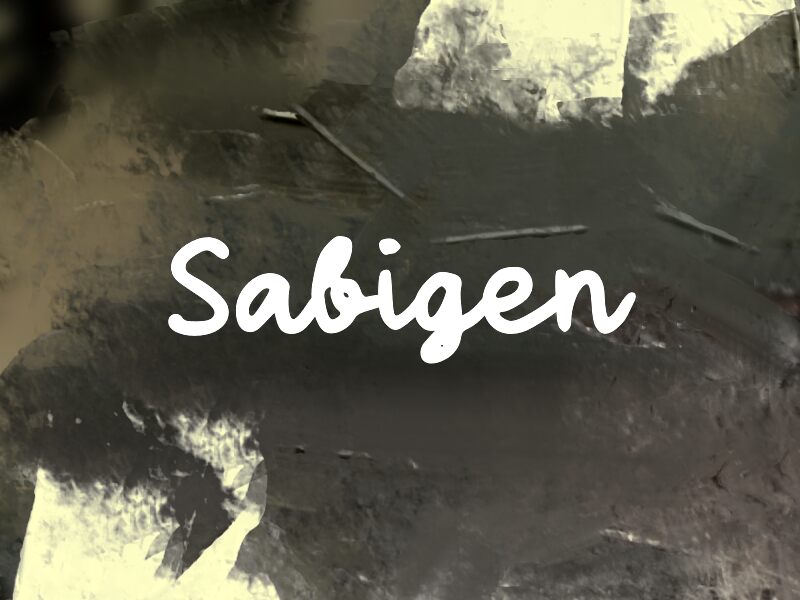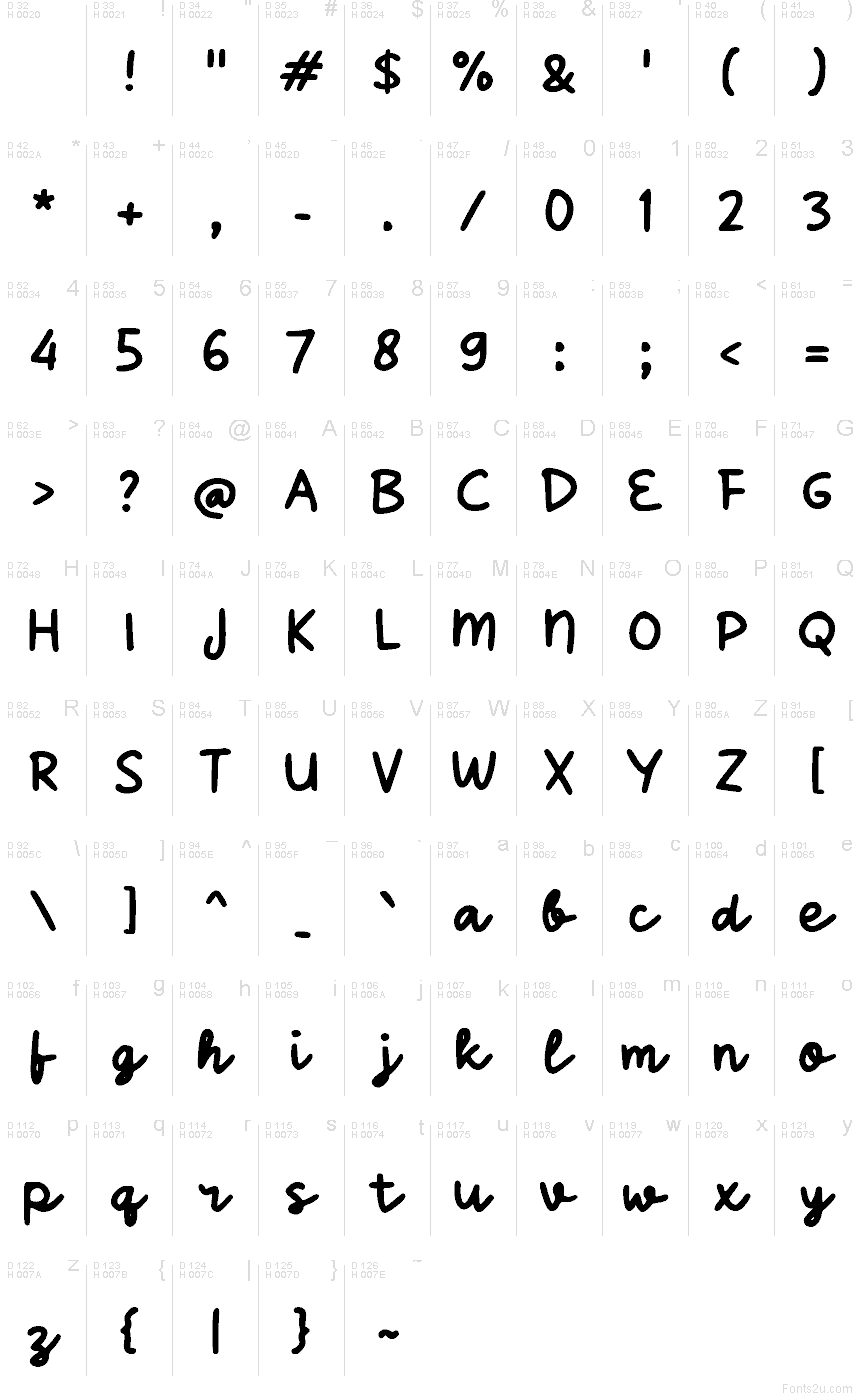
Sabigen
Sabigen 是由 Wep 设计的一款免费手写字体,其特色在于随性的笔刷脚本节奏,以及饱满圆润的线条感,令字形显得柔软而不生硬。字体在起伏间带有自然的跳跃感,加粗的笔画连接处给人一种快速马克笔书写的感觉,而非拘谨的精细书法。
这种灵动的韵律非常适合咖啡馆品牌、产品标签、社交媒体名言、贺卡以及休闲包装,在这些场景中,亲切的手写感比正式字体更具感染力。尤其在短标题和 Logo 设计中,字体的下沉式基线和丰满的曲线能有效地起到视觉引导作用,让设计充满个性和活力。